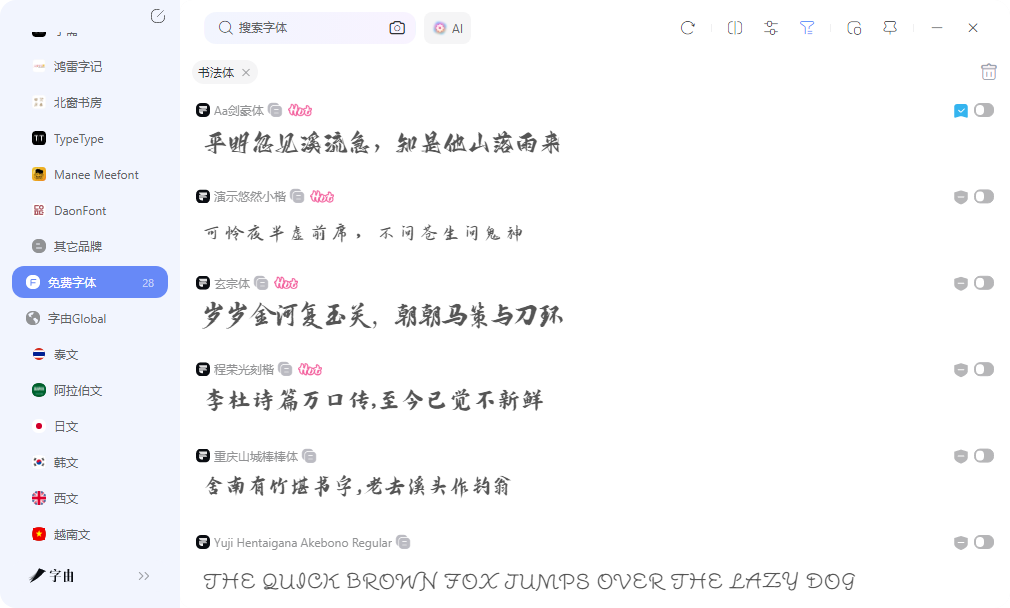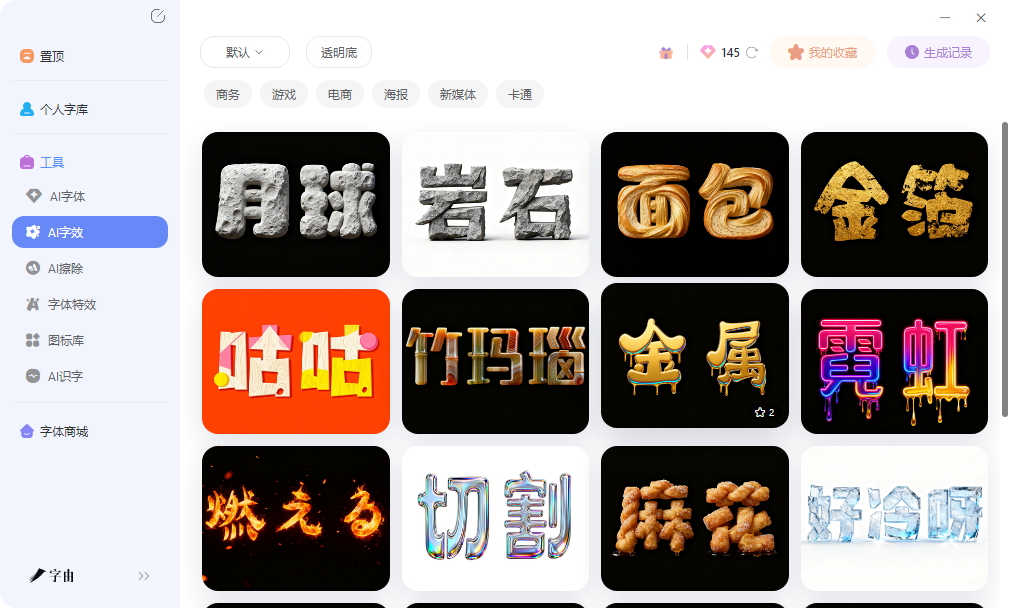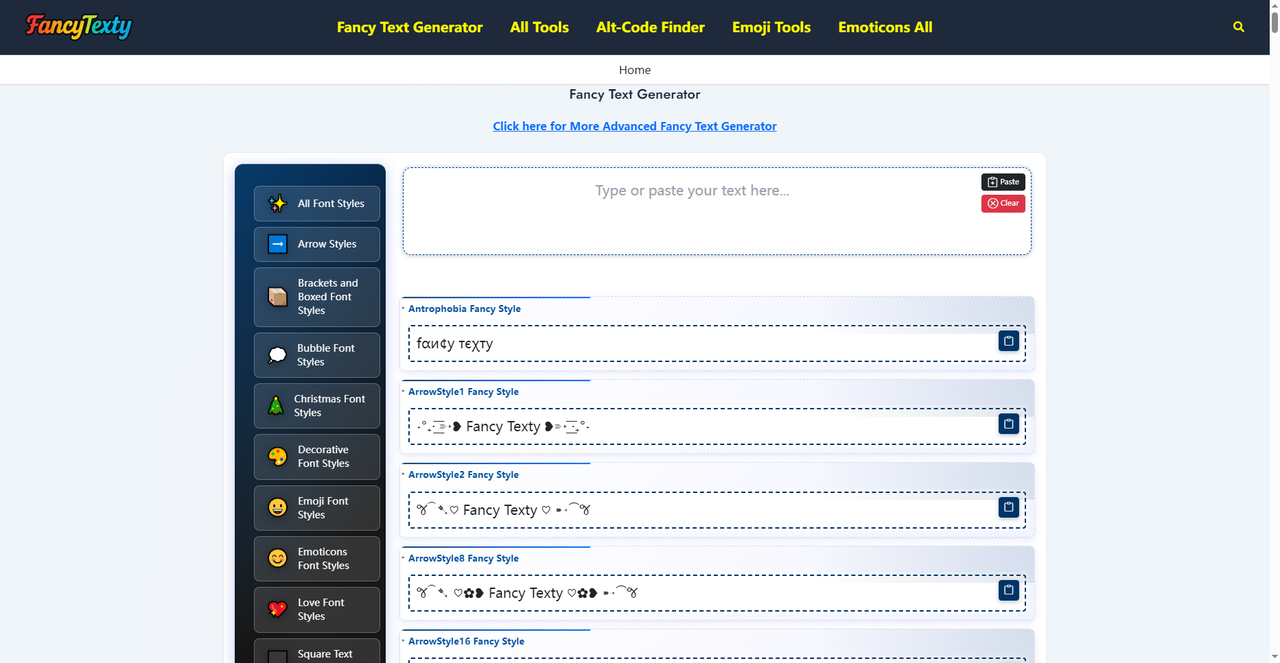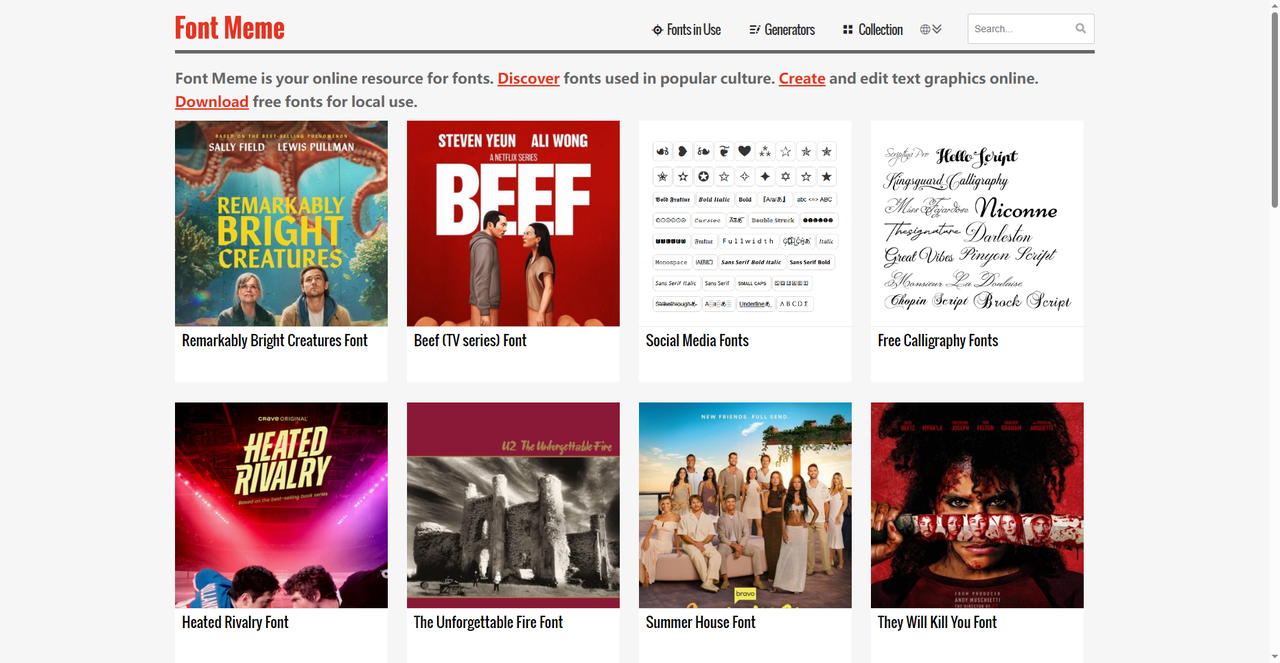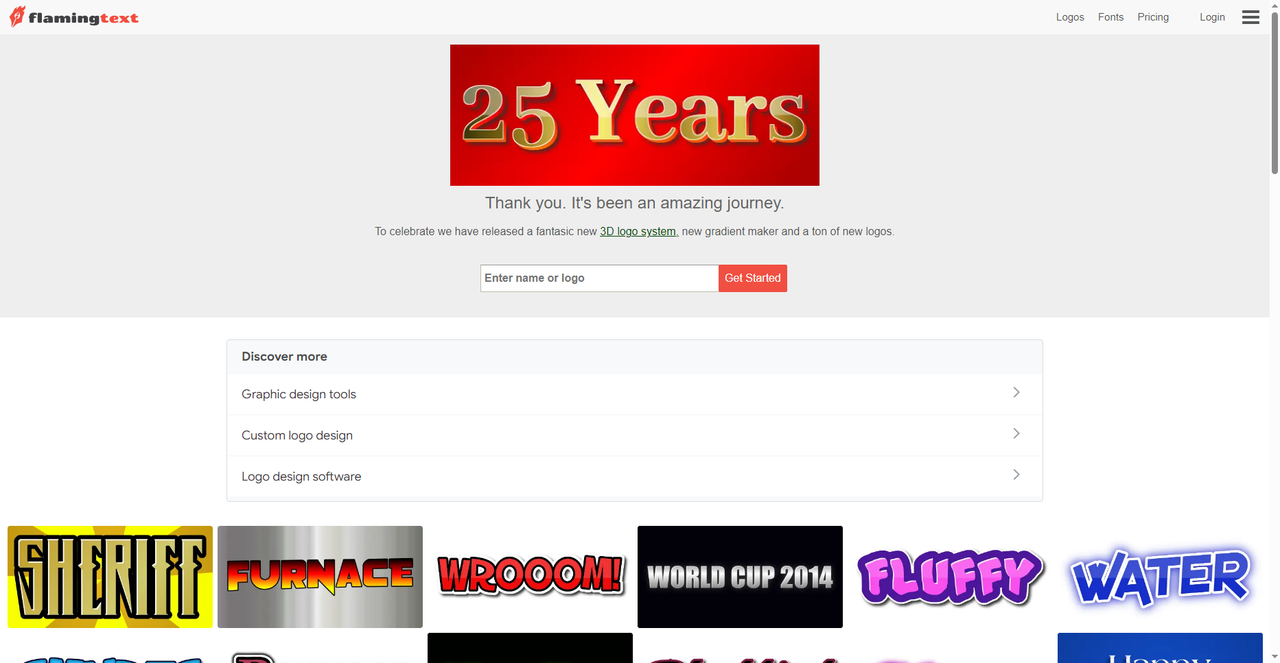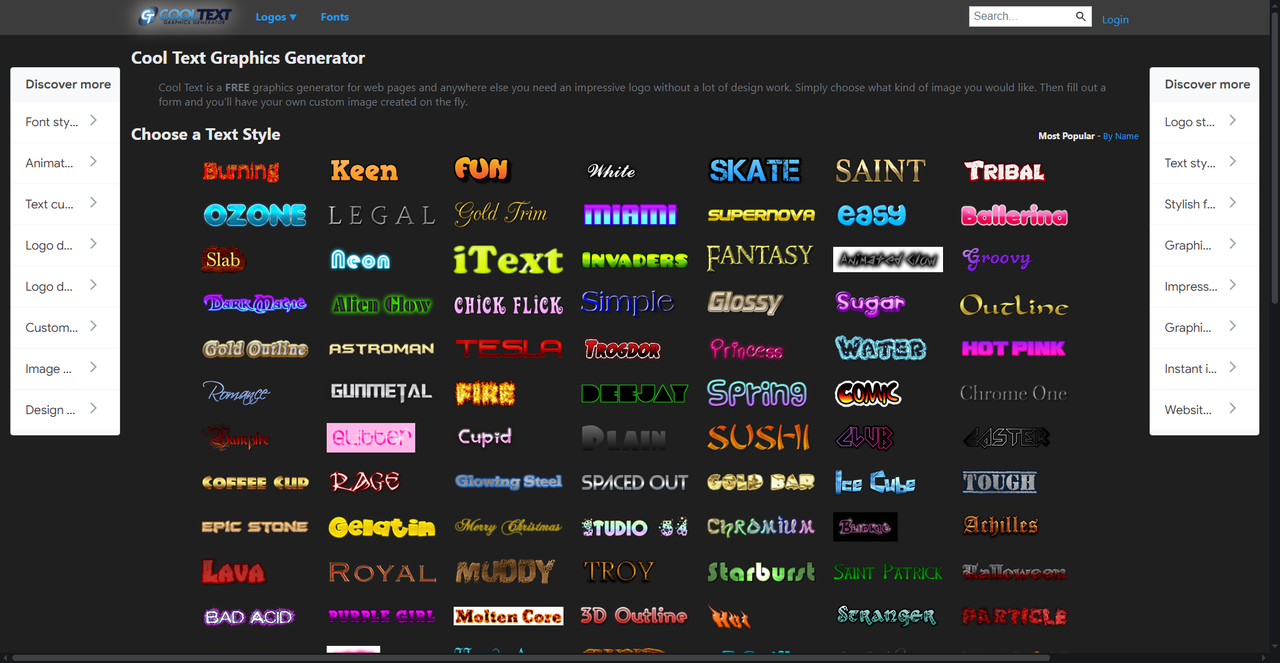
做设计不想用默认字体?这几个转换器直接收藏
打开PS或AI做海报时,标题文字往往是视觉重心,但系统默认的黑体、宋体、微软雅黑看久了难免审美疲劳。去字体网站下载安装新字体固然是个办法,可找字体、下文件、装到系统里再重启软件,这一套流程下来少说也要十几分钟。如果只是想快速出一张社交媒体配图、Banner标题或者PPT封面,直接在线做艺术字体转换明显更省事。
字由的定位不是单纯的艺术字生成器,而是围绕字体使用全流程提供支持。打开客户端后,字体库按风格做了细分,黑体、宋体、手写体、书法体、卡通体各自归类,找起来比较直观。目前收录的字体数量不少,其中明确标注免费商用的会单独分类,做商业项目时直接筛选这个分类,授权问题比较清晰。
遇到不确定用哪种风格的情况,可以借助AI配字功能上传参考图,系统会分析画面气质并推荐视觉上匹配的字体选项,省去反复试用的麻烦。比如上传一张国潮风海报,系统会优先推荐书法体和粗黑体;上传日系清新风格,则会推手写体或圆体,匹配效率比人工翻页找高不少。
如果项目需要文字本身带有发光、投影、金属或浮雕效果,字由的AI字效值得一试。输入文案后选择特效类型,调整颜色、强度、角度、背景透明度等参数,生成的是带透明背景的PNG图片,可以直接放进PS、AI、Sketch甚至PPT里。特效类型包括霓虹发光、金属拉丝、立体浮雕、投影阴影等常见效果,每种效果下还有细分变体可选。登录后会有一定免费额度,预览阶段不消耗,确认效果后再正式输出,对偶尔做几张图的用户比较友好。
2、Fancy Texty
Fancy Texty走的是Unicode花式字体转换路线,不是生成图片,而是把普通文字转换成特殊Unicode字符组合。输入中文或英文后,系统提供几十种花体、粗体、斜体、空心字、双线字、气泡字样式,一键复制就能粘贴到微博、小红书、抖音简介、朋友圈文案或者Telegram频道里。这种转换完全不消耗额度,打开网页就能用,适合需要快速美化社交媒体文案的场景。
因为是Unicode字符,在任何支持Unicode的平台上都能正常显示,手机、电脑、不同APP之间复制粘贴不会出现乱码。网站还提供了颜文字和特殊符号库,可以配合花式字体一起使用,让文案排版更有层次感。缺点是样式相对简单,没有立体或光影特效,更适合纯文字场景的装饰,不适合做海报标题。对于日常发动态、写简介、做社群运营、发邮件标题来说,Fancy Texty的轻便程度是图片生成工具比不了的,几秒钟就能让普通文案变得更有辨识度。
3、Font Meme
Font Meme的特色在于字体识别和风格复刻。网站收录了大量电影海报、游戏标题、品牌Logo使用的字体信息,上传参考图或选择作品名称,系统会告诉你用了什么字体,同时提供在线生成入口。输入自己的文案,就能套用某个经典电影或热门游戏标题的字体风格,比如科幻片的棱角无衬线体、复古海报的粗衬线体、日系游戏的像素风字体等。这个功能对做同人设计、致敬风格海报或者影视类自媒体封面很有帮助,生成的结果可以下载PNG,免费使用。
除了特效生成,Font Meme的字体百科部分也能查到字体的设计师、发布年份、字重数量和授权信息,选字体时更有依据。网站还设有字体识别论坛,上传图片后社区用户可以帮忙辨认字体名称,遇到冷门字体时这个互助功能很管用。Font Meme的生成界面相对简洁,参数调节不如Cool Text和FlamingText丰富,但风格辨识度极高,做主题性设计时直接套用省时省力。对于需要快速出图又追求风格统一的设计任务,Font Meme的现成模板是不错的起点。
4、FlamingText
FlamingText侧重Logo风格的艺术字生成,特效偏向火焰、霓虹、金属切割、激光、3D挤压等冲击力强的视觉效果。网站首页按风格做了分类导航,选择模板后进入编辑界面,输入文字内容,调整配色方案和光影角度,系统会实时更新预览图。除了静态PNG,FlamingText还支持导出GIF动画,适合做短视频封面、网页Banner或者Discord服务器头像,动态效果比静态图更能抓眼球,用在视频开头或直播间封面里,点击率通常比纯文字封面高出一截。
网站提供免费下载选项,但分辨率有限,高清版本和无水印导出需要付费。如果只是做社交媒体配图、PPT标题或者社团活动海报,免费尺寸完全够用。比较实用的一个功能是项目保存,生成后可以复制链接,下次打开直接修改文案或配色,不用重新调参数,做系列图时效率很高。另外,网站支持批量生成同风格不同文案的系列图片,做活动倒计时或系列海报时比较方便。FlamingText的特效偏向欧美风格,文字内容支持中文,但部分花体模板对中文字符的兼容性一般,建议优先用于英文标题或中英混排里的英文部分。
5、Cool Text
Cool Text是一个运营多年的在线艺术字生成网站,模板库覆盖了立体、金属、火焰、冰晶、涂鸦、木纹、大理石等几十种风格。进入首页后先选择模板分类,每个分类下又有多个变体,比如金属类就分黄金、铬合金、生锈铁等细分效果。输入文字内容后,系统会实时渲染预览,右侧可以调整主色、辅色、阴影深度、表面光泽、文字间距等参数,调好后点击下载即可。导出格式支持PNG和GIF,PNG带透明背景,直接拖到PS里就能继续排版,不需要额外抠图。对于赶时间的电商运营或自媒体人来说,这种即拿即用的体验很省心。
网页工具打开就能操作,Cool Text和FlamingText的模板库对做海报和封面比较友好,导出图片直接可用;Font Meme适合喜欢影视游戏风格的用户,复刻经典字体效果很省事;Fancy Texty则是日常社交文案的快捷美化方案。字由在字体管理和AI特效方面提供了更系统的支持,从选字体到出特效图都能在客户端内完成,商用授权标注也比较清晰。偶尔做几张图用网页工具足够,长期做设计可以搭配字由的字体库一起用,工作流更顺畅,效率会高不少。